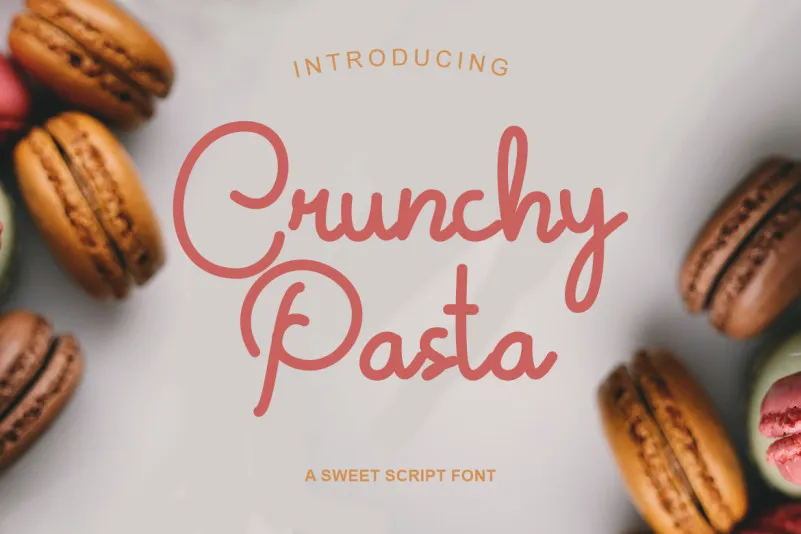
A fonte ‘Crunchy Pasta Script Font’ é uma sugestão perfeita para aqueles que desejam adicionar personalidade a seus projetos digitais. Ela se destaca por sua elegância simples e traços fortes, fornecendo um toque único e criativo sem comprometer a simplicidade do texto. Para designers de sites, livros de receitas ou até mesmo para quem busca uma fonte única em redes sociais, essa fonte oferece uma maneira encantadora de tornar qualquer projeto ainda mais especial. Seu designer, Heloyud, conseguiu criar um desenho à mão que não só é atraente visualmente, mas também adiciona uma sensação lúdica e descontraída ao seu trabalho. Ideal para quem busca um toque autêntico em seus projetos digitais sem comprometer a praticidade da leitura do texto.
Designer: Heloyud